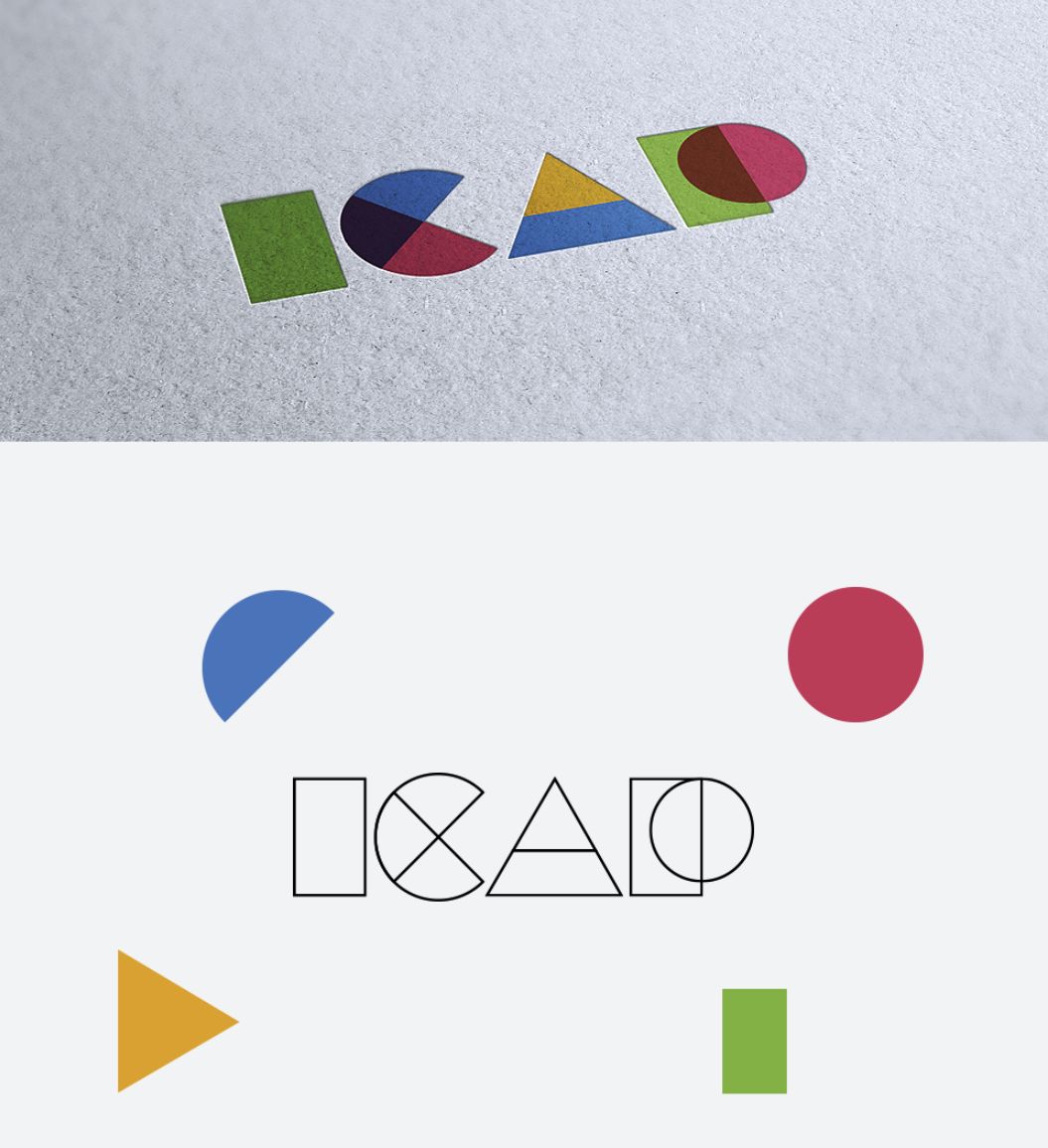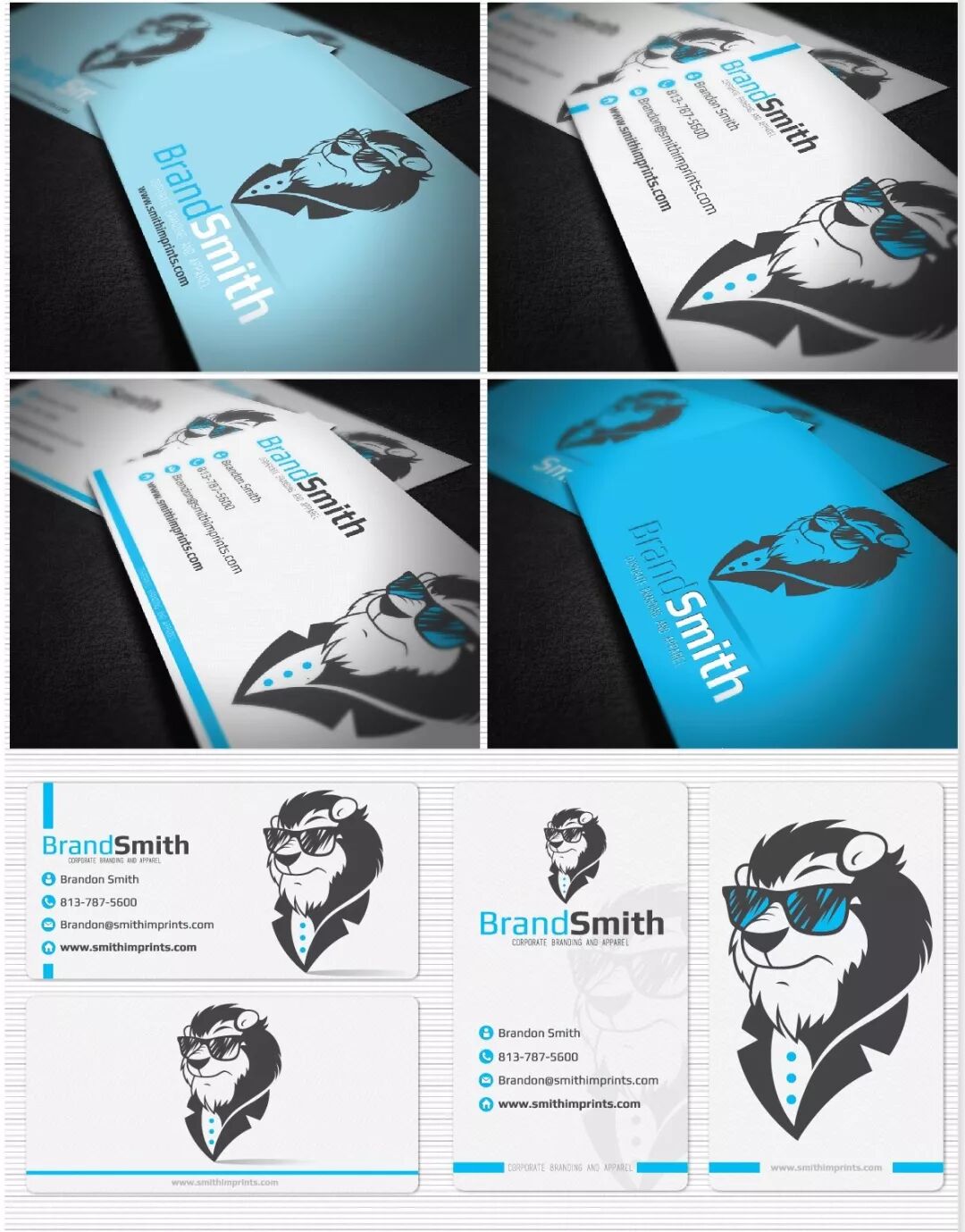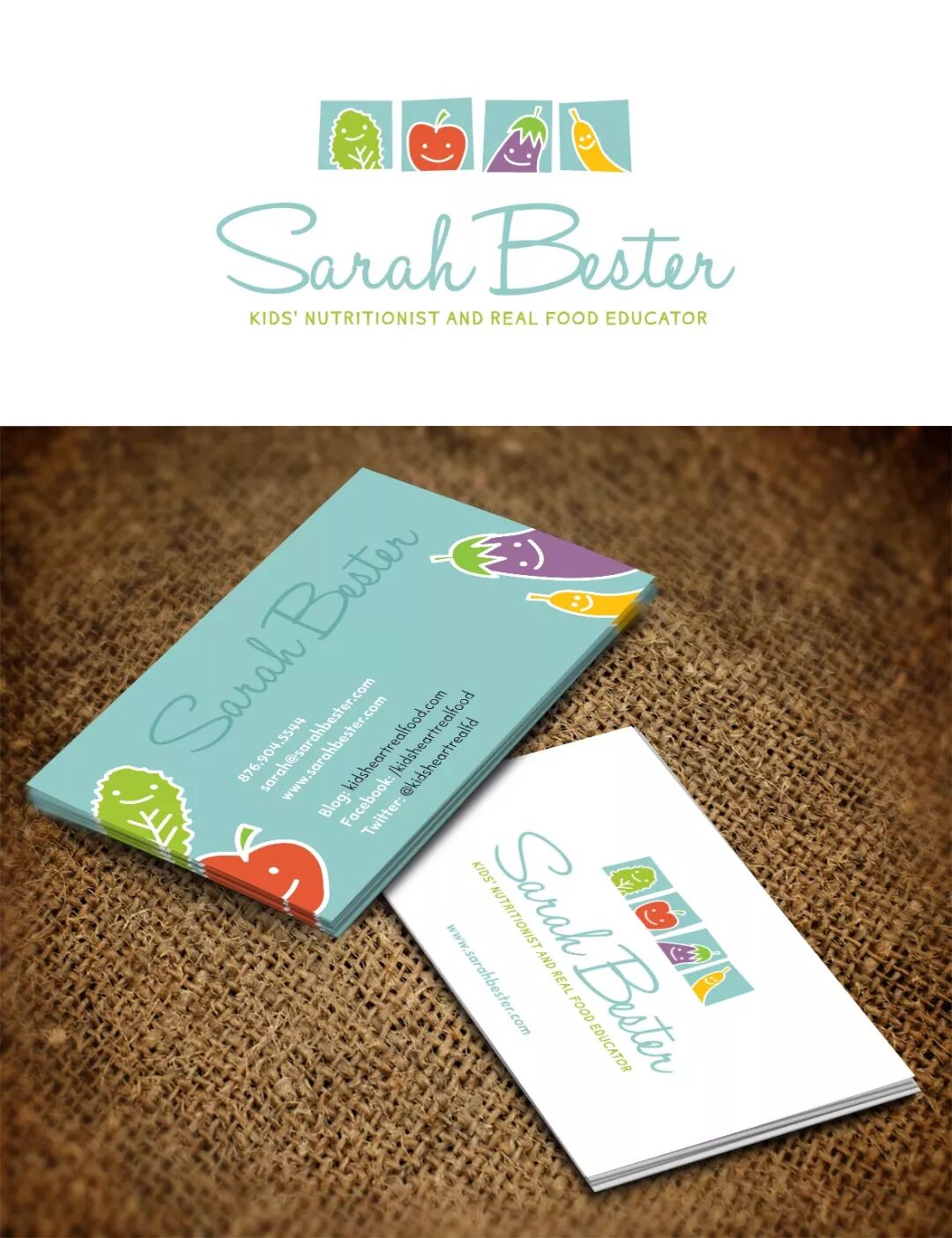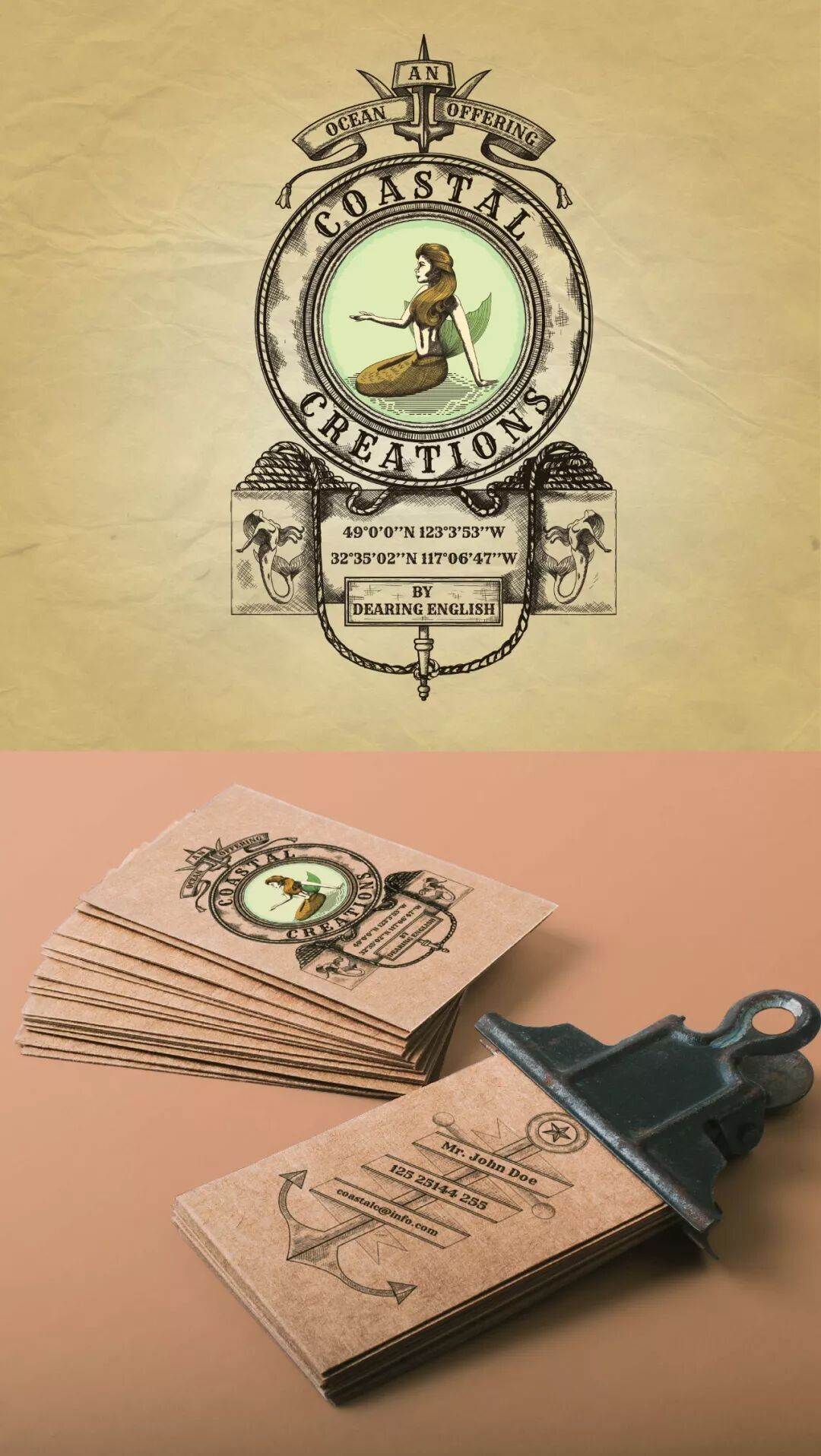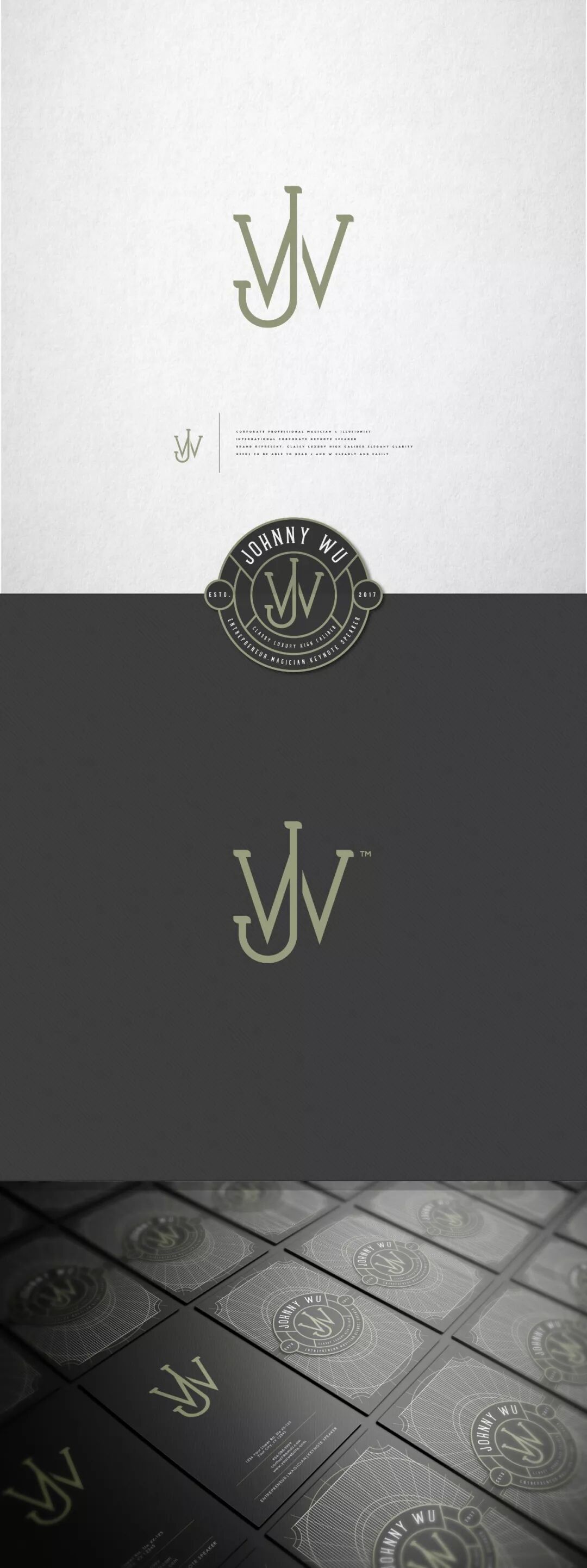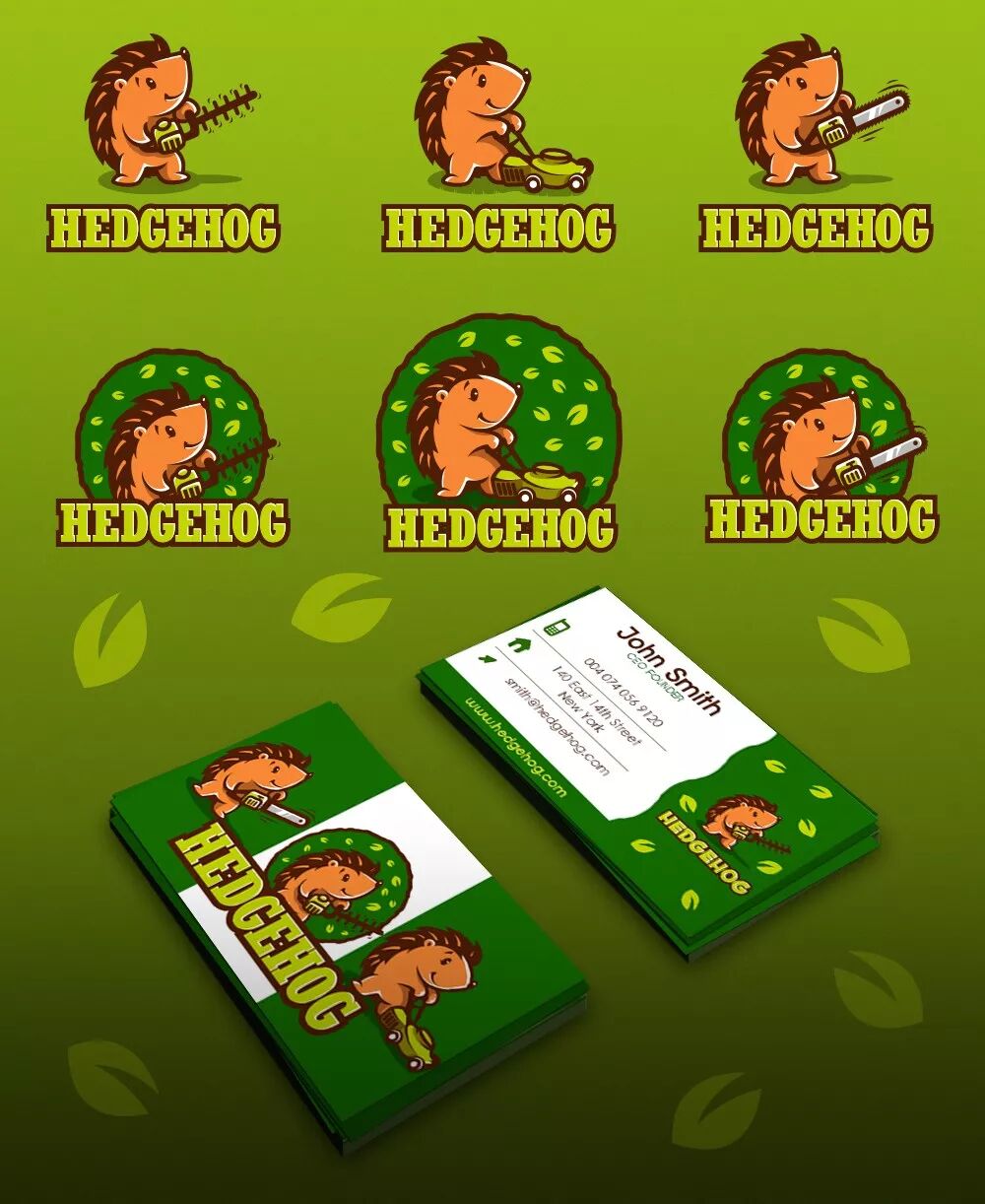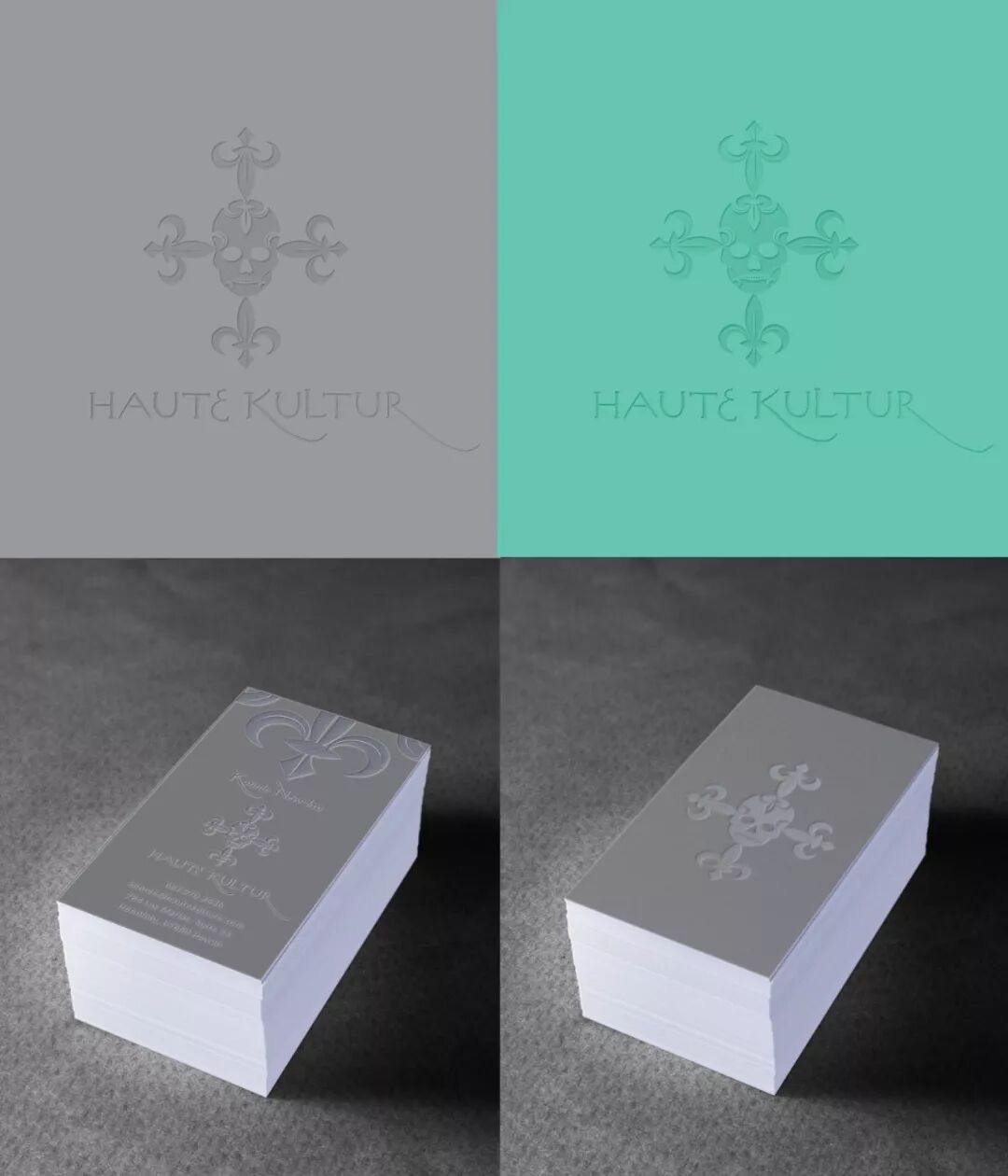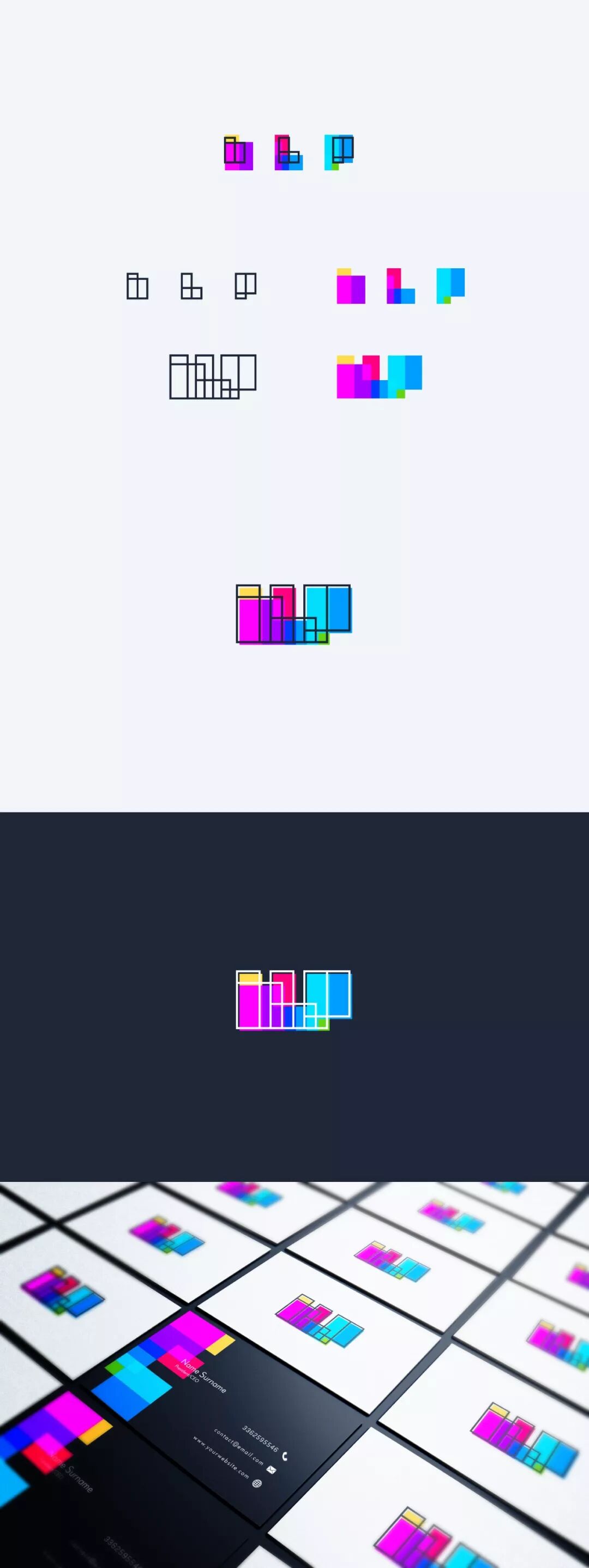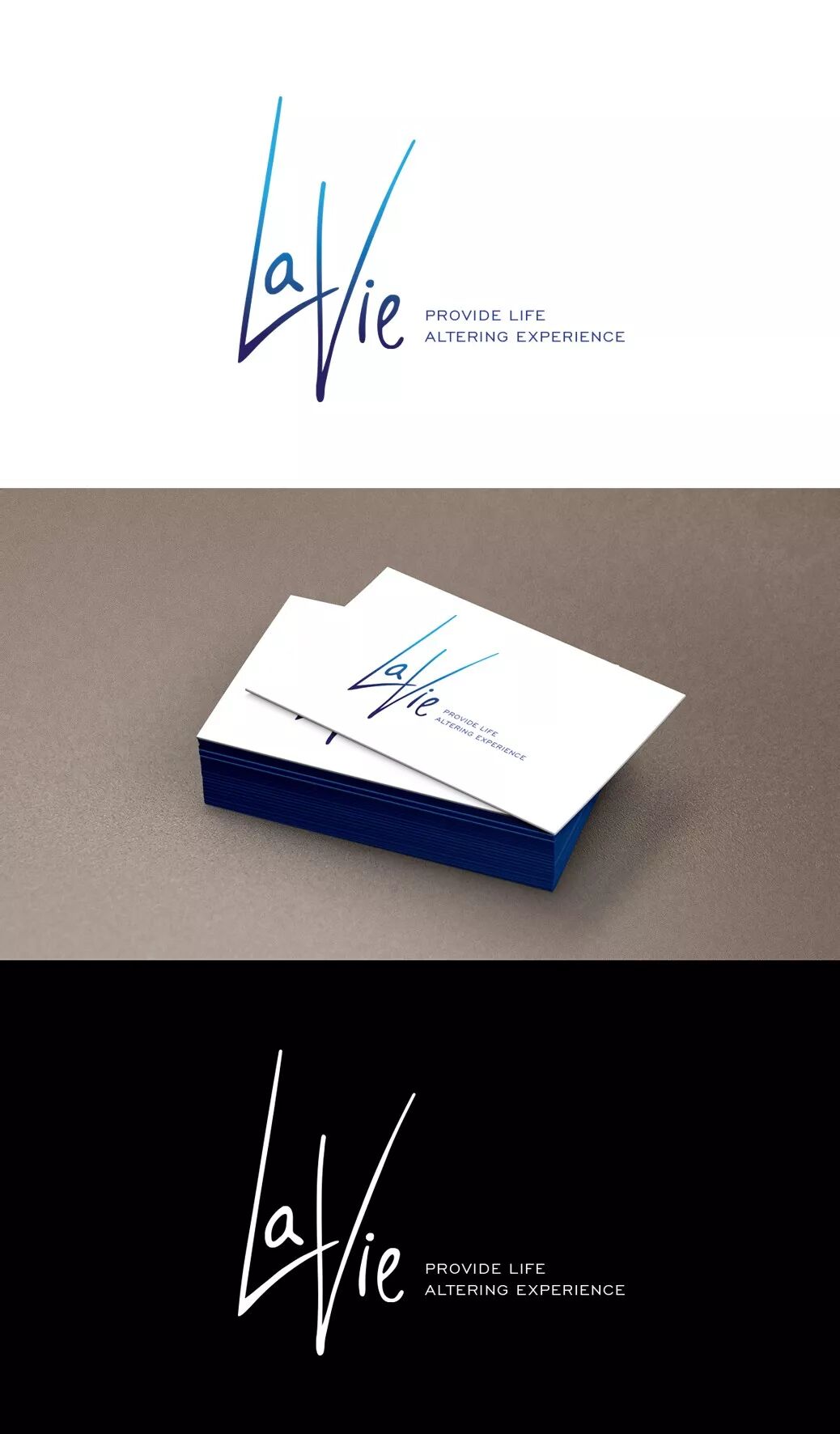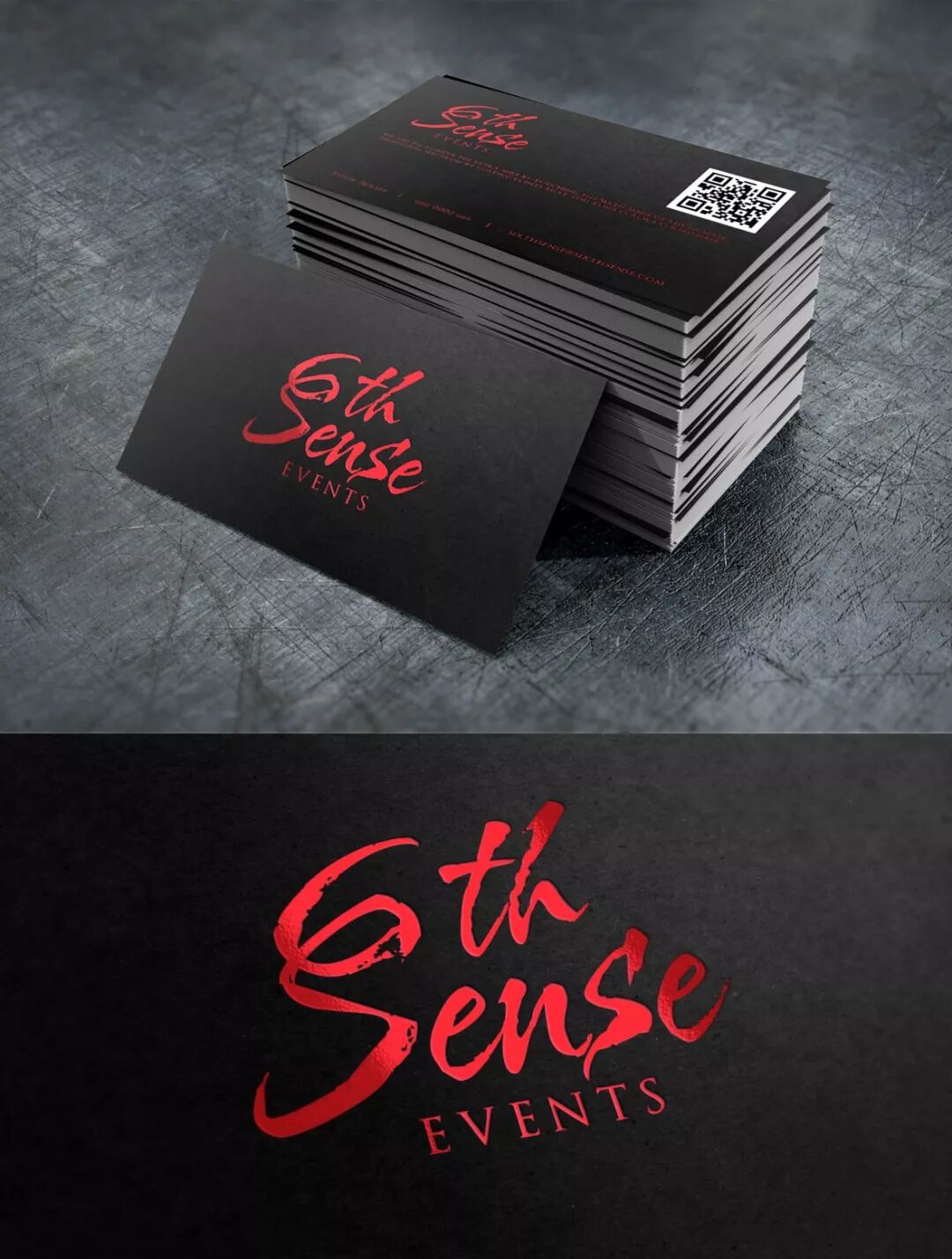
你做1000个设计,都不如这only one有竞争力!
又到年底了,各种年会、社交活动已经蓄势待发,除了准备各种战袍,有一个东西你是不是忽略了,那就是能让人记住你的名片。
有是有,就是太丑了,我都不想带出来。
平时老是给别人设计名片,没时间给自己弄。
现场加微信就好了,名片拿回去也是扔。
没有名片……
喂,别的行业就算了,你可是设计师,名片就代表你个人,你确定要这样自我埋没吗?
不过说真的,中国确实不如西方国家重视社交名片,其中有一个很重要的原因,就是不!好!看!要不就太正经,要不就太low,还美其名曰,要符合公司形象。
都8102年了,思想是不是得变变,每天那么多碎片化信息,人家凭什么想起你,很可能就是在某一天,一个特别的场合,你递了一张很有创意的名片,而这一眼,人家就巴巴地忘不了你~的名片。
所以今天柚子要好好给你开开眼,明年能不能升职加薪,召唤神龙,就看它了。
巧用萌系动物
每个公司可能都有一个卡通形象,或吉祥物,像字由就是小鸟,准确地说是海樱,所以给你们看看柚子的名片(ps过了,正式名片可不敢这样,哈哈)。
接下来我们看看Mad pepper的手绘作品,这是个小燕子,看着就很有艺术感。
而这个可爱的狗狗,来自新西兰某宠物食品公司。
也有这种形式表达我是pets,来自德国插画家Cross the Lime。
这不是蜜蜂,依然是狗,名片真的很喜欢汪星人呢~来自pecas。
3AM3I的设计更卡通,看了就忘不了这个魔性的蛙~哦不,壁虎。
而狮子的这个,感觉应用范围更广,猜得出这是给什么公司设计的吗?服装品牌,哈哈!
很喜欢设计师KreatanK的设计,颜色好看,刺猬也可爱。
最后一个是食品相关的,看着就很想舔屏,来自意大利设计师RaidenD。
用色彩吸引视觉
最近不止一次说过颜色,因为它是最能直接刺激视觉的,你想想工作了一天,感觉周围都是灰暗的,突然有一个色彩亮眼的东西出现在你面前,是不是整个人都醒了。
设计师KisaDesign为BLP做的名片,很简洁,但色彩搭配,很有逼格。
而goopanic也采用了几何图形,把它跟logo结合起来,像不像小时候的七巧板~
他还为医疗公司设计过名片,完全打破了冷冰冰的感觉,红绿搭配也是高难度了。
昨天刚说的珊瑚橙,这就可以用在名片上了,by pecas。
加入水彩元素,也是今年很流行的哦。
他还设计了儿童营养师的名片,很有趣吧,第一眼猜不到。
用字体点亮名片
想要名片好看,字体设计也是重中之重,可能所有的亮点,都集中在这上面了。
KisaDesign把w、j结合在一起,有一种复古的味道。
黑红搭配,也是名片中经常出现的,只是有了字体加持,更加有个性,by ultrastjarna。
她还为医生设计了一款金色名片,真是刷新了认知,国外的doctor都这么fashion的嘛?
有时候不需要太炫,只需用图标,替换一下字母,就很有设计感,by goopanic。
渐变色也可以用在字体上,by pecas。
不一样的材质
还有一种让别人注意的方法,就是变换材质,让人接触的第一瞬间,就感觉与众不同,视觉不够,触觉来凑!
浮雕感,高不高级,来自pecas。
他还设计了相片质地的名片,有了它,你还舍得丢掉嘛?
设计师by nnorth也做了一款更立体的名片,只是这个制造成本有点高吧?
喜欢这种做旧的布料感,感觉可以拿它擦镜头,哈哈,by goopanic。
信纸也不错,能让时光慢下来,by Mad pepper。
球迷一定喜欢这种磨砂质地,由Bravo公司为Jupiter Futbol(JPF)设计。
打破固有框架
谁说名片就该是方方正正的,你看字由的名片,不就突出来一个圆角嘛。不过这跟下面的设计师比起来,还是毛毛雨啦!
设计师Rose''设计了两款很形象的名片,你看得出它们是干嘛的吗?
还有很多异形名片,让你一次看个够。
好了,累死我了,最后给你们看一个日本神仙脑洞广告,100个人是如何交换名片,可以学学,哈哈哈!